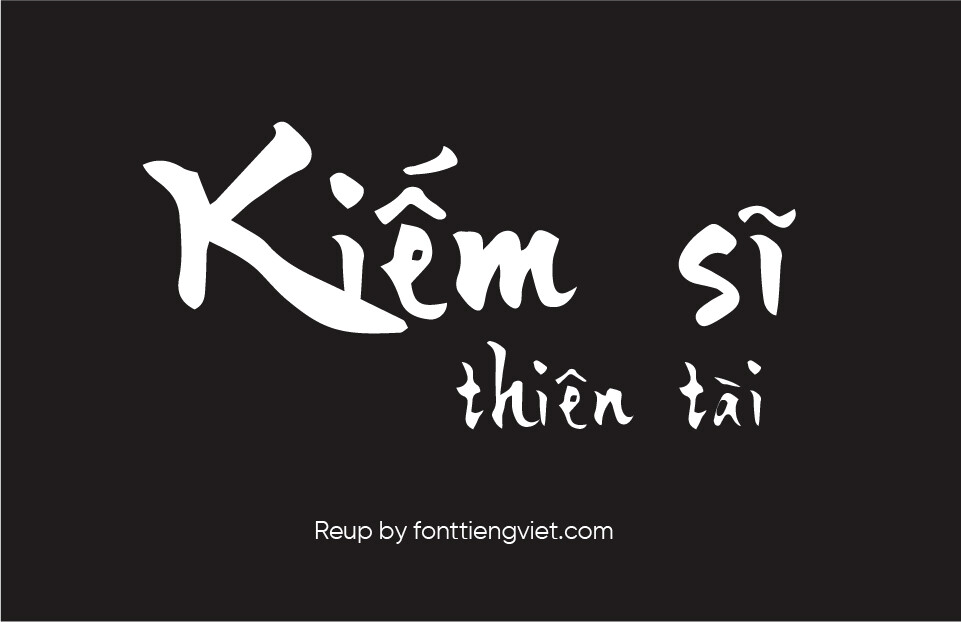
Trong thế giới thiết kế đồ họa và tài liệu học tập, việc lựa chọn một Font Chữ phù hợp đóng vai trò then chốt, không chỉ ảnh hưởng đến tính thẩm mỹ mà còn cải thiện trải nghiệm đọc. Gần đây, cộng đồng yêu thích typography, đặc biệt là các bạn học sinh và sinh viên, đã không ngừng săn lùng bộ phông chữ độc đáo mang tên Font Việt hóa MTD Yozakura JP. Đây là một tài sản quý giá cho những ai đang tìm kiếm sự kết hợp hoàn hảo giữa nét đẹp Á Đông tinh tế và khả năng hỗ trợ tiếng Việt đầy đủ. Bộ font này không chỉ giúp các tài liệu ôn thi, luận văn hay các bài thuyết trình trở nên nổi bật mà còn đảm bảo tính chuyên nghiệp cao. Nếu bạn là một nhà thiết kế, một giáo viên hay một học sinh trung học đang chuẩn bị cho kỳ thi tốt nghiệp, việc tìm hiểu về font chữ đẹp và tiện ích này là điều vô cùng cần thiết.
Sự ra đời của phiên bản Việt hóa đã giải quyết triệt để các vấn đề về lỗi dấu, lỗi kerning thường gặp ở các font gốc tiếng Nhật, mang lại sự mượt mà và liền mạch tuyệt vời khi sử dụng trong môi trường ngôn ngữ Việt Nam. Hãy cùng chúng tôi khám phá sâu hơn về lý do tại sao Font Việt hóa MTD Yozakura JP lại được ưu ái đến vậy trong lĩnh vực giáo dục và thiết kế.
Giới Thiệu Chung về Font Việt hóa MTD Yozakura JP và Nguồn Gốc
Font MTD Yozakura JP ban đầu là một phông chữ tiếng Nhật (JP) mang phong cách viết tay thư pháp, gợi lên hình ảnh hoa anh đào (Yozakura – hoa anh đào đêm) rực rỡ và lãng mạn. Với các nét chữ mềm mại, uyển chuyển nhưng vẫn giữ được độ rõ ràng cần thiết, phông chữ này nhanh chóng thu hút sự chú ý của giới thiết kế quốc tế. Tuy nhiên, đối với người dùng tiếng Việt, việc sử dụng phông chữ gốc gặp nhiều hạn chế do thiếu các ký tự dấu và độ tương thích thấp.
Chính vì lẽ đó, các chuyên gia về typography đã tiến hành “Việt hóa” bộ font này. Quá trình Việt hóa không chỉ đơn thuần là thêm dấu mà còn là việc tinh chỉnh kỹ lưỡng từng glyph, đảm bảo rằng các ký tự tiếng Việt, từ ă, â, đ, ê, ô, ơ, ư đến các dấu thanh (sắc, huyền, hỏi, ngã, nặng), đều hiển thị hoàn hảo và hài hòa với tổng thể thiết kế. Sự chăm chút này đã biến Font Việt hóa MTD Yozakura JP thành một công cụ mạnh mẽ, đáp ứng được các tiêu chuẩn khắt khe nhất của các dự án học thuật và đồ họa.
Phiên bản Việt hóa này giữ nguyên được tinh thần nghệ thuật của bản gốc, tạo ra một cảm giác vừa cổ điển vừa hiện đại, rất thích hợp để làm tiêu đề ấn tượng cho các bài báo khoa học, hoặc thiết kế bìa sách giáo khoa, sổ tay học tập.
Lý Do Font MTD Yozakura JP Trở Nên Phổ Biến Trong Giới Học Sinh
Môi trường học đường đòi hỏi các tài liệu phải vừa dễ đọc, vừa có tính thẩm mỹ để kích thích sự hứng thú của học sinh. Font Việt hóa MTD Yozakura JP đáp ứng xuất sắc cả hai yêu cầu này, khiến nó trở thành lựa chọn hàng đầu cho các bạn học sinh trung học phổ thông, sinh viên và giáo viên khi soạn thảo các văn bản quan trọng.
Đặc Điểm Thiết Kế: Sự Kết Hợp Giữa Truyền Thống và Hiện Đại
Yozakura JP có một đặc điểm độc đáo là các nét chữ được thiết kế với độ dày mỏng không đồng đều, mô phỏng lại nét bút lông mềm mại. Điều này tạo ra sự khác biệt lớn so với các font chữ tiêu chuẩn (như Times New Roman hay Arial) vốn được xem là cứng nhắc và nhàm chán. Dù mang hơi hướng thư pháp, font vẫn giữ được độ rõ nét cao, giúp mắt người đọc không bị mệt mỏi khi tiếp xúc với văn bản dài. Đây là lợi thế tuyệt vời khi thiết kế các tài liệu ôn thi đại học hoặc cẩm nang học tập.
Ứng Dụng Thực Tế Trong Tài Liệu Ôn Thi và Luận Văn
Đối với học sinh chuẩn bị cho các kỳ thi quan trọng như kỳ thi tốt nghiệp trung học phổ thông quốc gia hay các kỳ thi học sinh giỏi, việc trình bày đẹp mắt có thể gián tiếp thể hiện sự nghiêm túc và chuyên nghiệp. Font MTD Yozakura JP thường được sử dụng để:
- Thiết kế tiêu đề chính, tiêu đề phụ trong các bài tiểu luận, giúp phân biệt rõ ràng các phần.
- Tạo điểm nhấn cho các câu trích dẫn quan trọng hoặc công thức toán học, vật lý.
- Làm slide thuyết trình học tập (PowerPoint, Google Slides) thêm sinh động và thu hút, đặc biệt là trong các môn xã hội hoặc nghệ thuật.
- Thiết kế các ấn phẩm ngoại khóa như bảng tin trường học, thiệp mời sự kiện tốt nghiệp.
Khả năng hiển thị tuyệt vời trên cả màn hình kỹ thuật số và bản in chất lượng cao khiến nó trở thành một công cụ đa năng cho mọi nhu cầu học tập và sáng tạo.
Rõ ràng, Font Việt hóa MTD Yozakura JP không chỉ là một phông chữ, mà là một công cụ hỗ trợ đắc lực trong hành trình học tập và sáng tạo, đặc biệt trong bối cảnh các yêu cầu về thẩm mỹ tài liệu ngày càng cao. Từ việc chuẩn bị tài liệu ôn thi cấp tốc đến việc hoàn thiện một bản luận văn tốt nghiệp xuất sắc, sự tinh tế của Yozakura JP chắc chắn sẽ để lại ấn tượng mạnh mẽ. Sự kết hợp giữa nghệ thuật Nhật Bản và khả năng hỗ trợ ngôn ngữ Việt hoàn hảo đã tạo nên một bộ font không thể thiếu trong thư viện của bất kỳ ai làm việc liên quan đến thiết kế và giáo dục. Đừng chần chừ, hãy nhanh chóng tìm và tải bộ Font Chữ tuyệt vời này để làm phong phú thêm kho tài nguyên thiết kế của bạn ngay hôm nay, giúp các em học sinh tự tin chinh phục mọi kỳ thi với tài liệu trình bày đẹp mắt và chuyên nghiệp nhất.